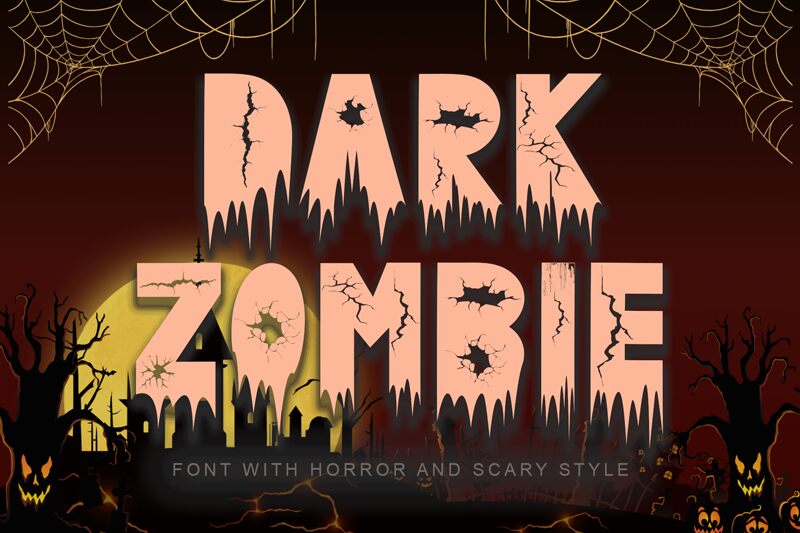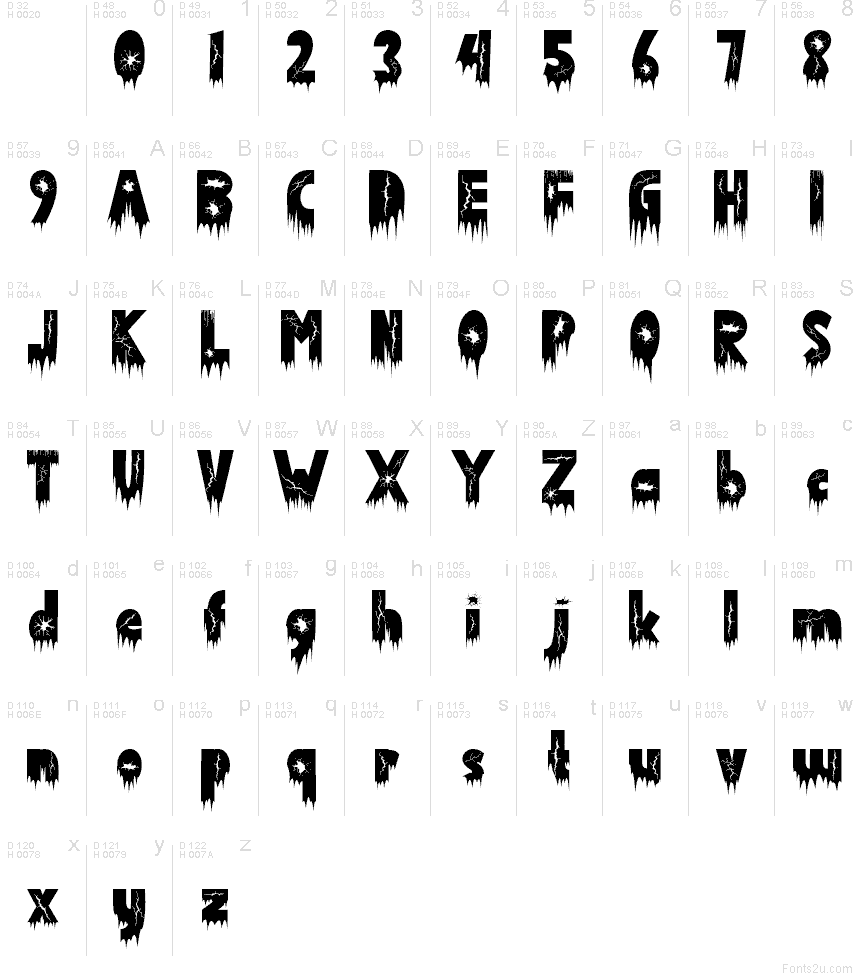
Dark Zombie
Dark Zombie de Yoga Letter es una tipografía display gratuita de estilo terror con trazos agrietados, bordes desgarrados y una base que gotea, dando a cada letra un acabado herido y zombi. Los cortes irregulares que recorren sus formas le otorgan un aspecto inquietante y rugoso, con una textura afilada de horror que hace justicia a su nombre.
Dark Zombie funciona muy bien en pósteres de Halloween, títulos de películas de terror, folletos de casas encantadas, banners de juegos, logotipos temáticos y gráficos espeluznantes para redes sociales. Esta tipografía gratuita aporta un toque deteriorado y siniestro a textos cortos donde las formas fracturadas y los detalles que gotean marcan el ambiente por sí solos.